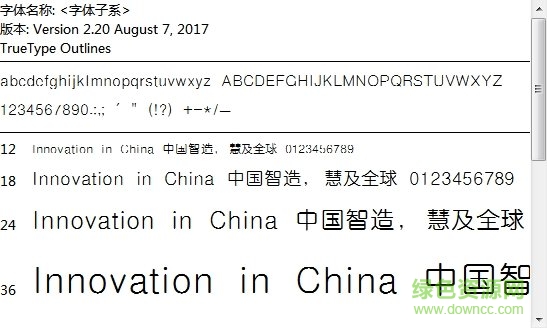
奶包的雨晴字體其實就是慧心的雨晴體,是一款下筆細(xì)膩、書寫秀氣的藝術(shù)字體,線條明朗而端正,讓你在閱讀時倍感溫馨,快來綠色資源網(wǎng)下載收藏吧!
慧心雨晴體,即奶包雨晴體,筆畫端正而清晰可變,與我們熟知的微軟字體比較類似,但在細(xì)節(jié)處有著明顯的創(chuàng)新,給文字更多個性特色,讓你的藝術(shù)更加怡然大方。
雨晴體字庫完整,能滿足大家的日程工作和學(xué)習(xí)需要,字跡精簡便于閱讀,讓你的圖書排版、藝術(shù)創(chuàng)意、平面設(shè)計更加深入人心。